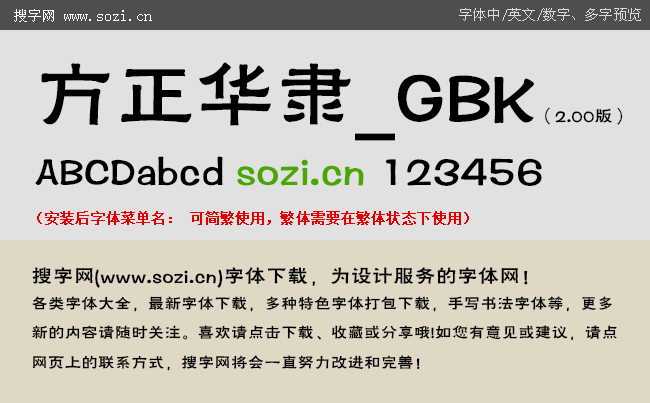
方正華隸_GBK
搜字網(wǎng)提供一款方正華隸_GBK中文字體下載,方正華隸_GBK是一款應(yīng)用于設(shè)計(jì)方面的中文簡體漢字,該字體形像氣質(zhì)佳,大方得體,并且整體效果十分出眾,GBK碼包含字體更全,適合應(yīng)用于廣告設(shè)計(jì)、名片設(shè)計(jì)、包裝印刷、兒童產(chǎn)品設(shè)計(jì)等應(yīng)用。